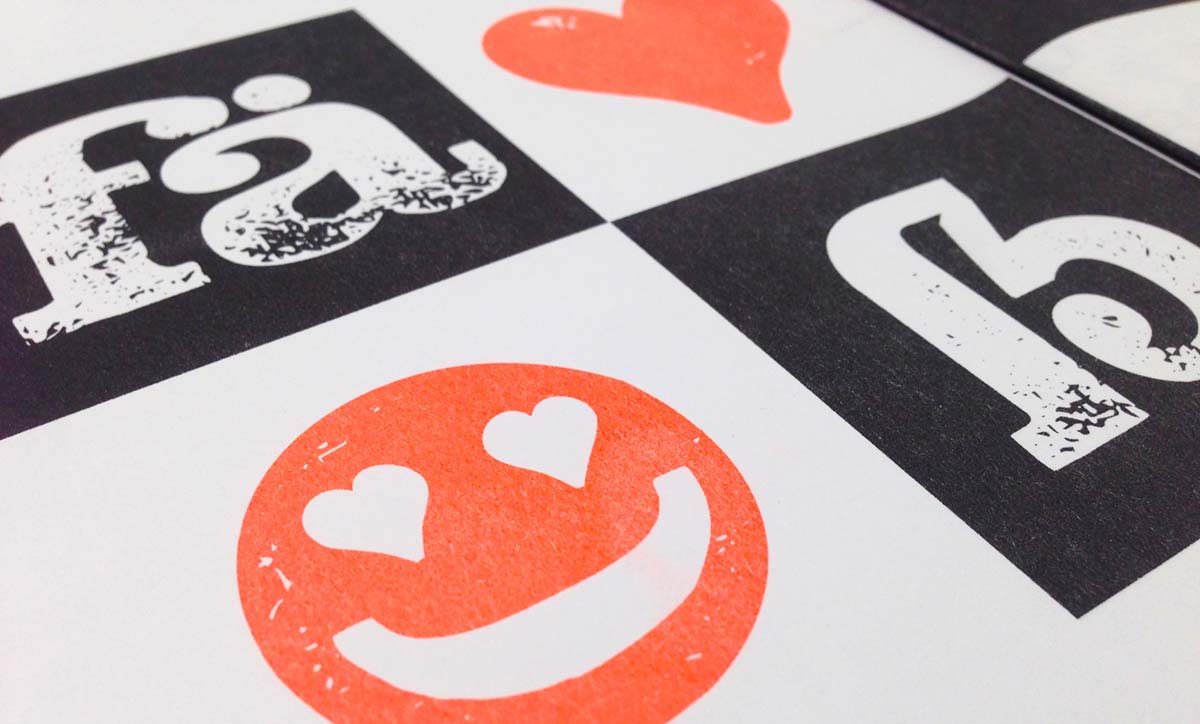
Verlosung: Schriftmusterheft im Riso-Print
Endlich mal wieder eine Verlosung im Fontblog. Der Berliner Schriftentwerfer Manuel Viergutz (typographicdesign.de) war so nett, mir 3 Exemplare seines neuen, 16-seitigen Schriftmuster-Büchleins »Hand Stamp Slab Serif Rough« zu überreichen. Ein gestalterischer und drucktechnischer Leckerbissen:
Und natürlich ist auch der Font, um den es geht, ein Highlight: Hand Stamp Slab Serif Rough , eine Slab-Serif-Displayschrift für den Headline-Einsatz. Ihr Zeichensatz basiert auf echten … Verlosung: Schriftmusterheft im Riso-Print weiterlesen